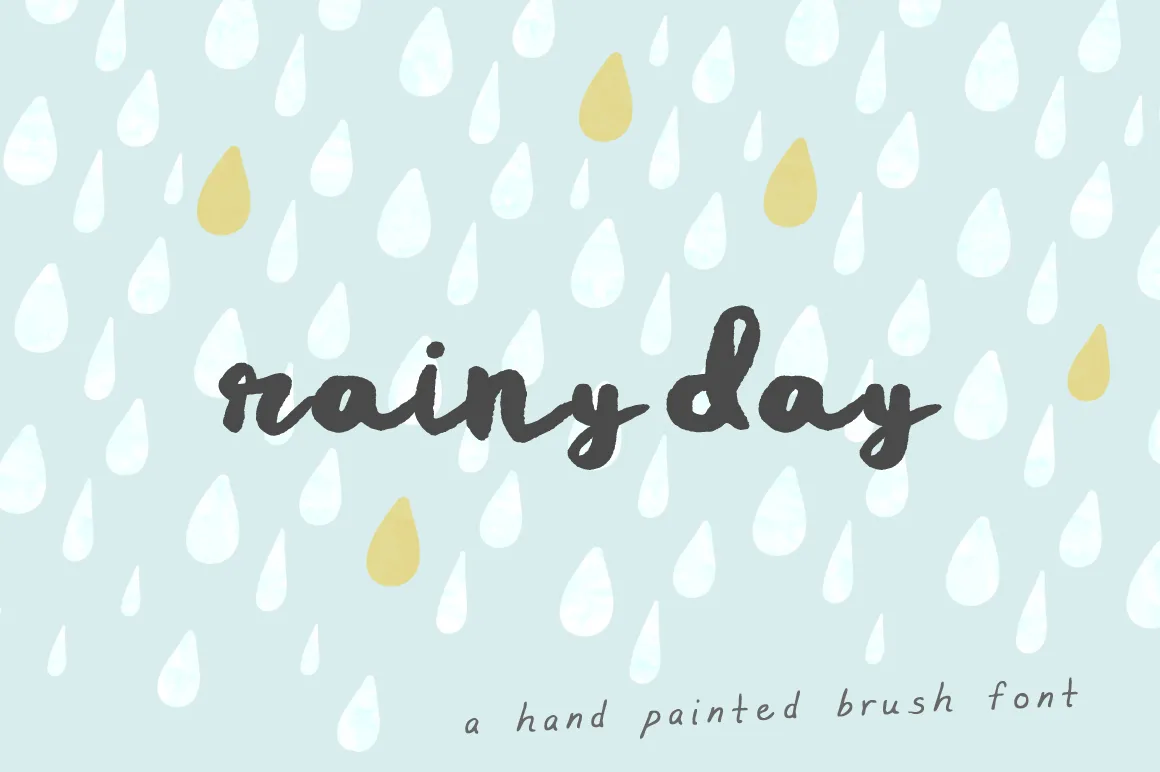
Rainy Day Font – Download Grátis
Rainy Day Font é uma beleza na forma de uma fonte esparadrapada, pintada a mão. Inspirado no design de Hamilton, esta fonte brush se destaca pelo seu estilo imprevisto, marcado por contornos rústicos e sem falhas. Ideal para projetos de design variados, como capas de livros, painéis de propaganda ou até mesmo um logotipo, a Rainy Day Font oferece um toque único que enriquecerá qualquer projeto visual. Seja ele uma delicada tipografia de texto ou uma impressionante borda em sua arte digital, é impossível não se apaixonar por esse brilho peculiar e autêntico da fonte brush.